Bộ font SVN với 465 kiểu chữ đã được Việt hóa hoàn chỉnh là một trong những tài nguyên thiết kế đồ họa quan trọng nhất hiện nay cho người dùng Việt Nam. Với khả năng hỗ trợ đầy đủ tiếng Việt có dấu, kiểu dáng đa dạng và chuyên nghiệp, bộ font này đặc biệt phù hợp cho mọi lĩnh vực thiết kế từ branding, in ấn, banner đến trình chiếu hoặc thiết kế kỹ thuật số.
Font SVN được phát triển và Việt hóa bởi STYLEno.1 Fonts – nhóm font designer nổi tiếng trong cộng đồng thiết kế Việt, chuyên tạo ra các bộ font vừa đảm bảo thẩm mỹ vừa chuẩn ngôn ngữ tiếng Việt. Mục tiêu của bài viết này là giúp bạn hiểu rõ bộ font này có gì đặc biệt, tại sao nên tải, và cách sử dụng hiệu quả nhất trong công việc sáng tạo.
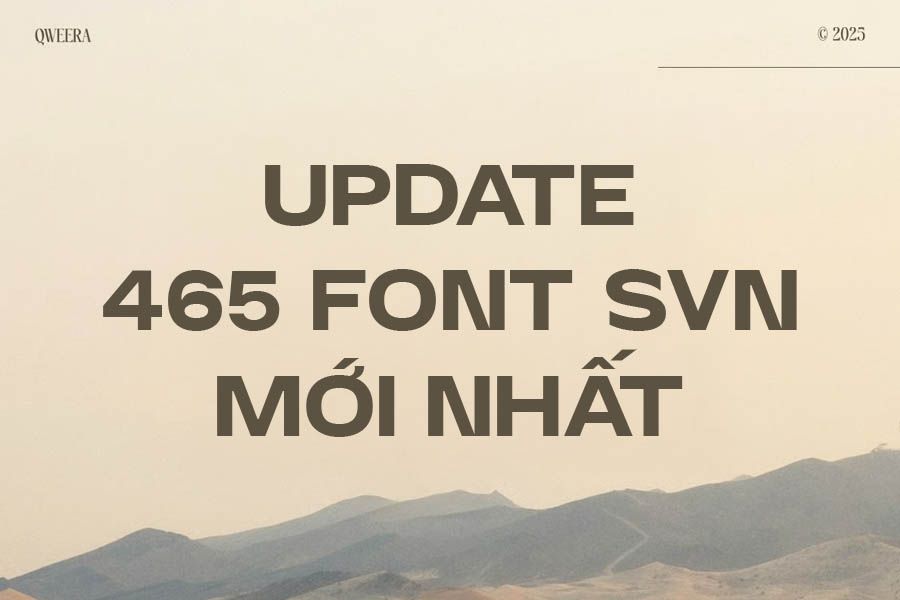
Font SVN là những bộ chữ được Việt hóa bởi nhóm STYLEno.1 Fonts, thường có tiền tố "SVN" trong tên như SVN-Gilroy, SVN-Avo. Những font này được chỉnh sửa lại để hỗ trợ đầy đủ bảng ký tự tiếng Việt, bao gồm các dấu, chữ cái đặc biệt như ă, â, ê, đ...
Được Việt hóa tỉ mỉ và nhất quán, font SVN mang lại trải nghiệm mượt mà khi sử dụng cho thiết kế in ấn hoặc digital. Ngoài ra, độ tương thích cao với các phần mềm đồ họa như Photoshop, Illustrator, Canva... khiến nó trở thành lựa chọn hàng đầu của cộng đồng thiết kế.
Font SVN được yêu thích bởi nhiều lý do thuyết phục. Trước hết, bộ font này sở hữu kho kiểu chữ phong phú với thiết kế đẹp mắt, đáp ứng đa dạng nhu cầu thẩm mỹ từ hiện đại, tối giản đến cổ điển hay phá cách. Không chỉ dừng lại ở vẻ ngoài, mỗi font trong bộ đều được tinh chỉnh kỹ lưỡng để phù hợp với ngữ âm và cấu trúc đặc trưng của tiếng Việt, đảm bảo hiển thị chính xác mọi dấu và ký tự. Bên cạnh đó, tính linh hoạt cao giúp Font SVN dễ dàng ứng dụng trong nhiều lĩnh vực như thiết kế thương hiệu, in ấn, truyền thông, đến các sản phẩm kỹ thuật số, làm cho nó trở thành lựa chọn hàng đầu của giới sáng tạo tại Việt Nam.
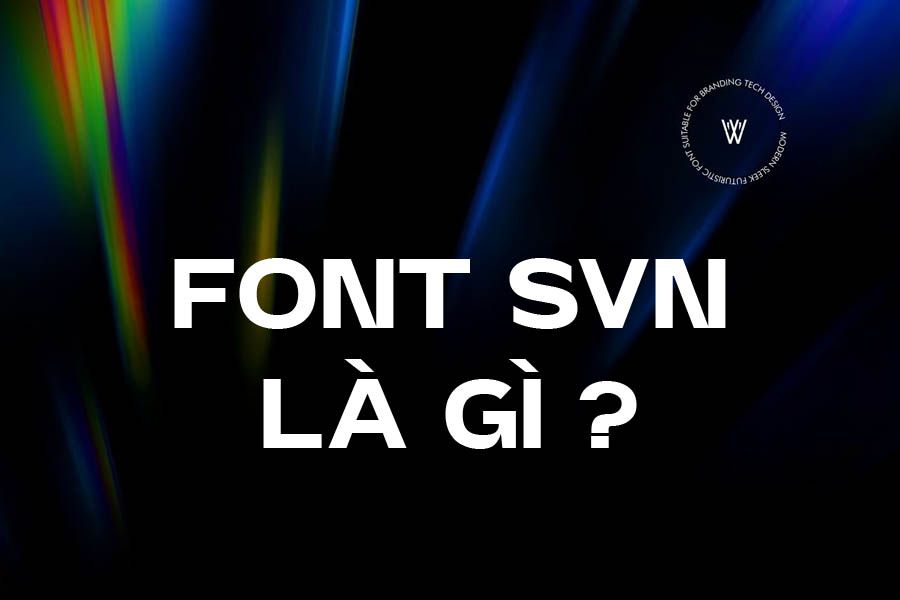
Bộ font SVN sở hữu nhiều kiểu sans-serif hiện đại, nổi bật với các cái tên như SVN-Avo, SVN-Gilroy và SVN-Bebas Neue. Nhóm font này có đặc điểm là thiết kế không chân, chữ thẳng, độ dày đồng đều và dễ đọc. Đây là lựa chọn lý tưởng cho thiết kế logo, banner quảng cáo, poster hiện đại hoặc giao diện startup công nghệ.
SVN Gratelos: Font chữ hiện đại với kiểu dáng không chân, các đường nét mạnh mẽ và sắc sảo. Các ký tự có kết cấu chắc chắn, gợi cảm giác chuyên nghiệp, nam tính và rất dễ định hình trong thiết kế thương hiệu hoặc các sản phẩm in ấn cao cấp. Font được thiết kế bởi Aluyeah Studio
SVN Megante: Megante là một font sans-serif mang tinh thần thanh lịch, nhẹ nhàng với các đường cong tinh tế, khoảng cách ký tự cân đối. Nét chữ cao, thoáng khiến nó phù hợp cho các thiết kế mang phong cách thời trang, tạp chí hoặc sản phẩm đòi hỏi sự sang trọng. Font được phát triển bởi Ardyana Types
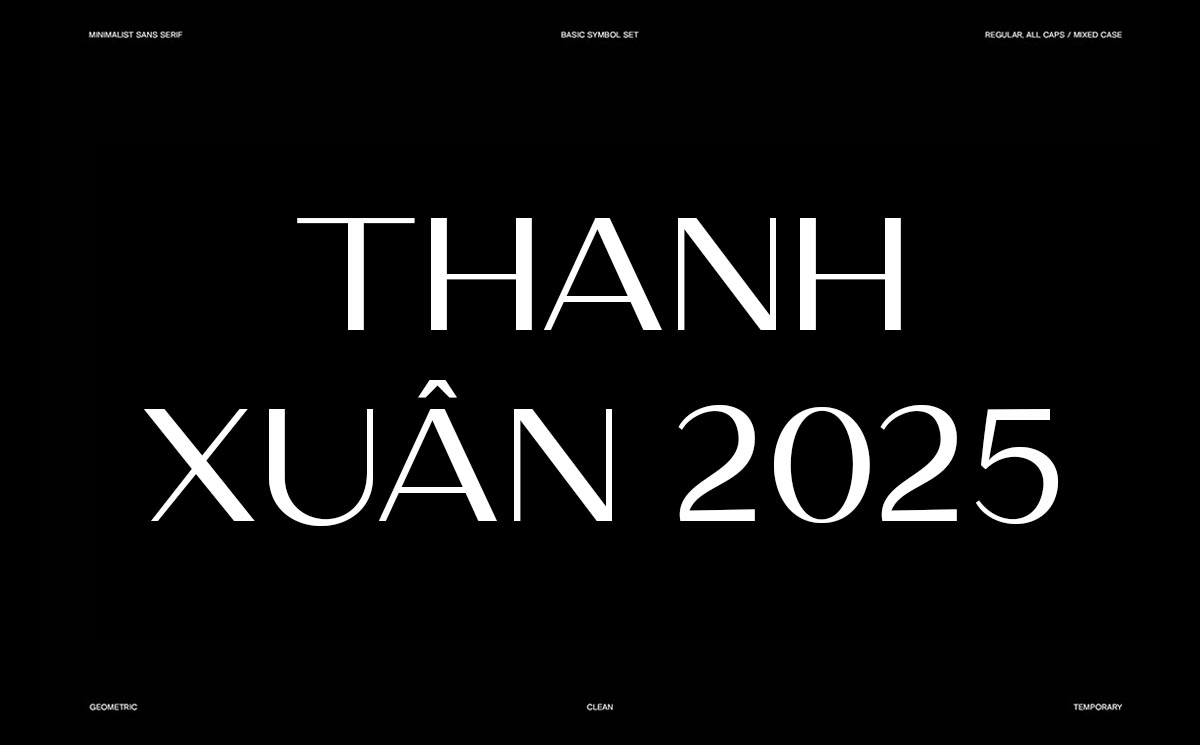
SVN Saudagar: Đây là font sans-serif có thiết kế trung tính, phù hợp cho cả tiêu đề lẫn đoạn văn. Nét chữ gọn, độ dày vừa phải, đường cong nhẹ giúp tăng tính thân thiện và dễ đọc. Font gốc do Storytype Studio phát hành
SVN Gilroy: Gilroy là một bộ font sans-serif hiện đại nổi tiếng với 20 style từ Thin đến Black. Thiết kế hình học gọn gàng, ổn định giúp nó thích hợp với nhiều mục đích sử dụng từ logo, tiêu đề đến ứng dụng di động. Font gốc của Radomir Tinkov
SVN Audrey: Audrey mang phong cách sans-serif thanh lịch pha lẫn nét nữ tính nhờ các đường cong bo tròn mềm mại. Font này có thể ứng dụng cho các thiết kế thời trang, mỹ phẩm hoặc giao diện web cao cấp. Tác giả font là Cristina Pagnotta
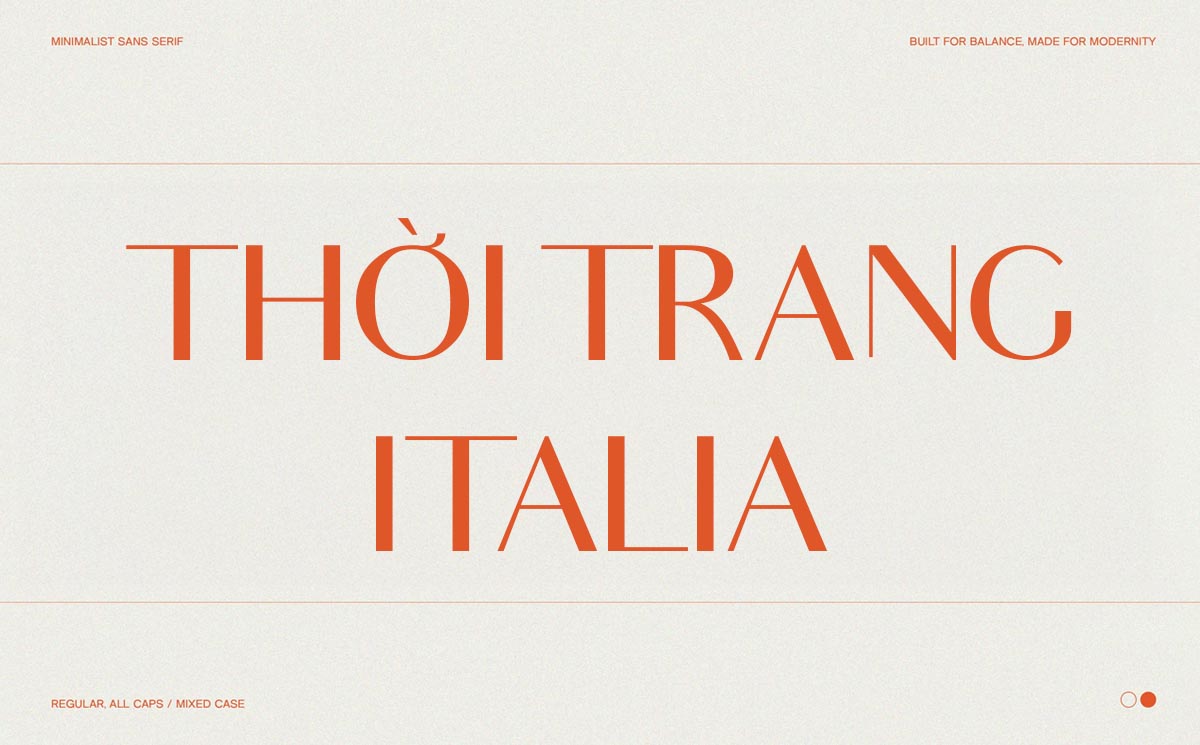
SVN Le Murmure: Le Murmure mang tinh thần tối giản đặc trưng của các font hiện đại châu Âu. Đường nét sắc mảnh, cao thoáng và mang vẻ đẹp sang trọng, phù hợp cho branding hoặc editorial design. Font gốc của Mathieu Desjardins
Với chân chữ rõ nét, độ tương phản cao giữa nét dày – mảnh, nhóm font serif cổ điển rất phù hợp cho các thiết kế mang tính học thuật, in ấn, xuất bản, hoặc tạp chí sang trọng.
SVN Canopee: Font serif mạnh mẽ và thanh lịch, với các đường nét đậm mảnh rõ ràng và chân chữ sắc sảo. Thiết kế lấy cảm hứng từ typography cổ điển châu Âu nhưng mang hơi thở đương đại, phù hợp tiêu đề tạp chí hoặc bao bì cao cấp. Font gốc do VJ Type thiết kế
SVN Heimer: Heimer là một font serif vintage mang lại cảm giác retro với chân chữ to bản, các đường cong dày dặn và cấu trúc chắc khỏe. Kiểu dáng này rất phù hợp cho thiết kế bìa sách hoặc poster cổ điển. Font được thiết kế bởi Storytype Studio
SVN Bahud Aroyek: Với kết cấu đặc trưng của font serif retro, Bahud Aroyek có phần chân chữ sắc nhọn và phần thân in đậm, tạo nên vẻ uy nghiêm và mạnh mẽ. Font này phù hợp cho thiết kế vintage, quảng cáo cổ điển và nhãn hiệu cao cấp. Tác giả: Letterhend Studio
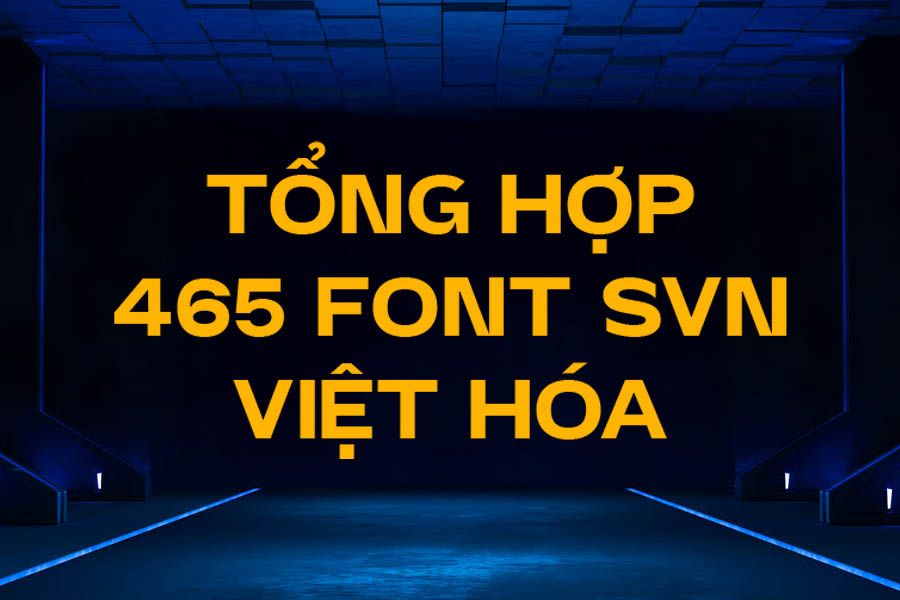
Font SVN là lựa chọn toàn diện cho thiết kế tiếng Việt hiện đại: hỗ trợ Unicode, dễ cài, đa dạng phong cách và miễn phí. Tuy nhiên, tránh:
Dùng quá nhiều font trong một thiết kế
Chọn sai font với mục đích (ví dụ dùng display cho văn bản dài)
Hãy lựa chọn đúng và tận dụng bộ 465 font SVN một cách thông minh – sáng tạo của bạn sẽ chuyên nghiệp hơn bao giờ hết.